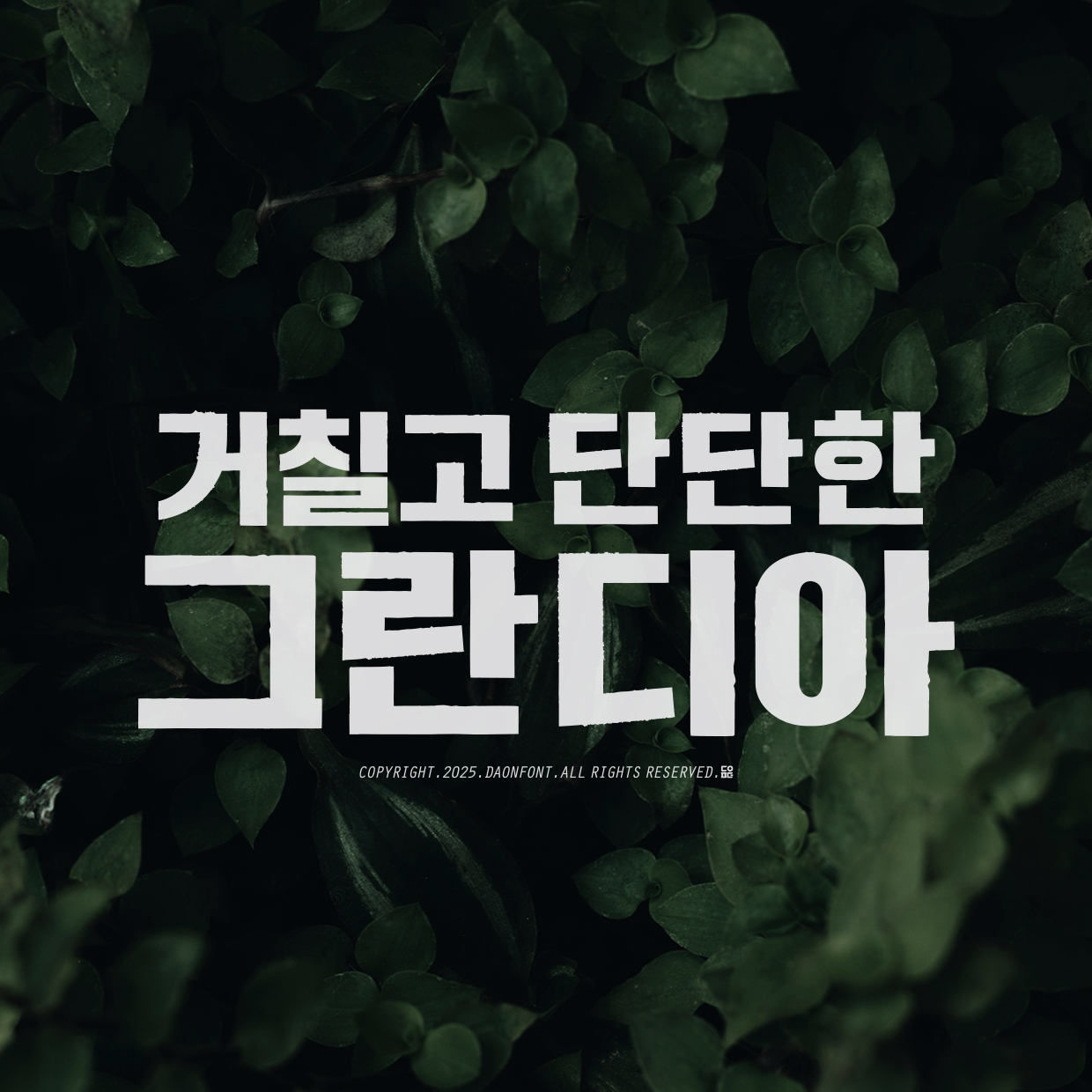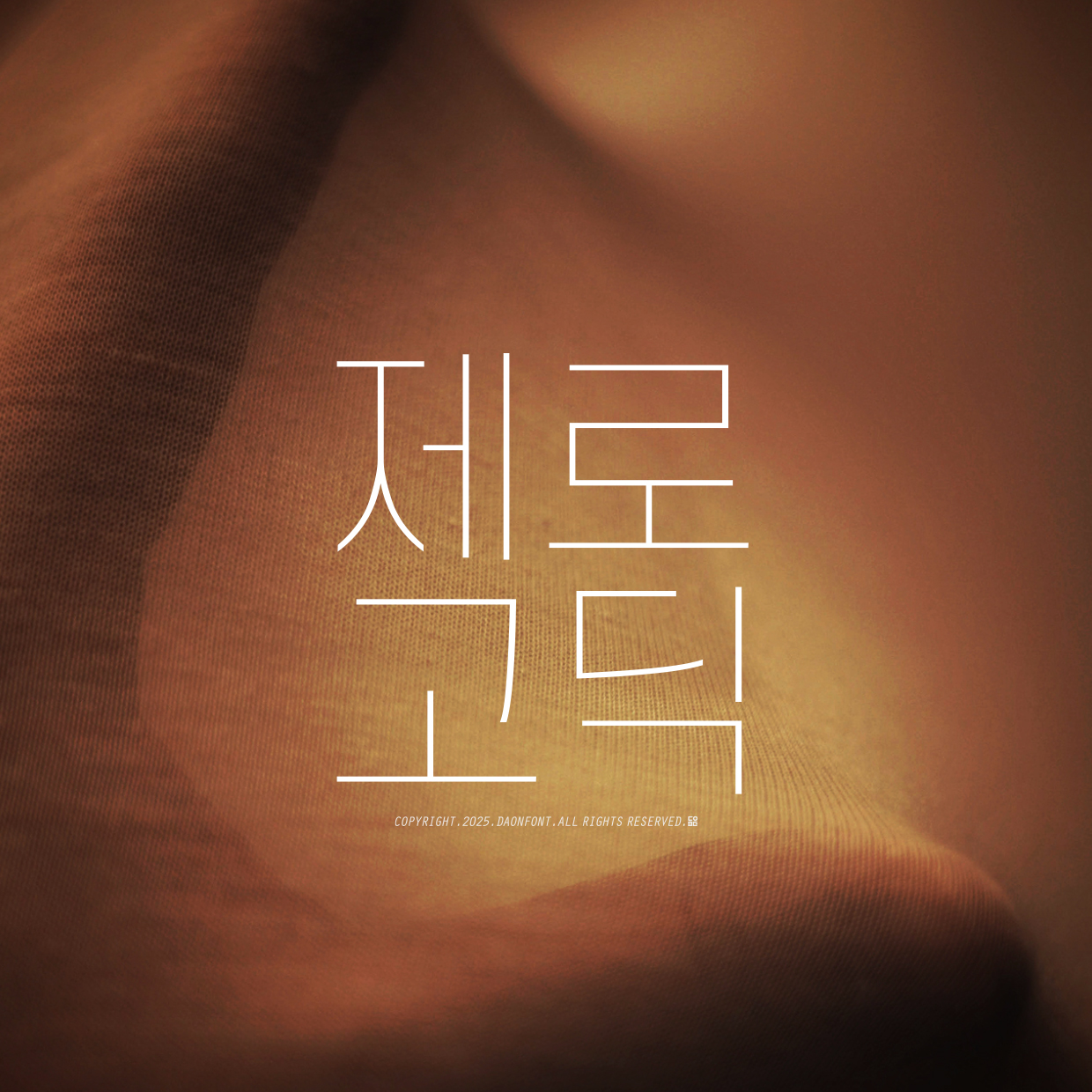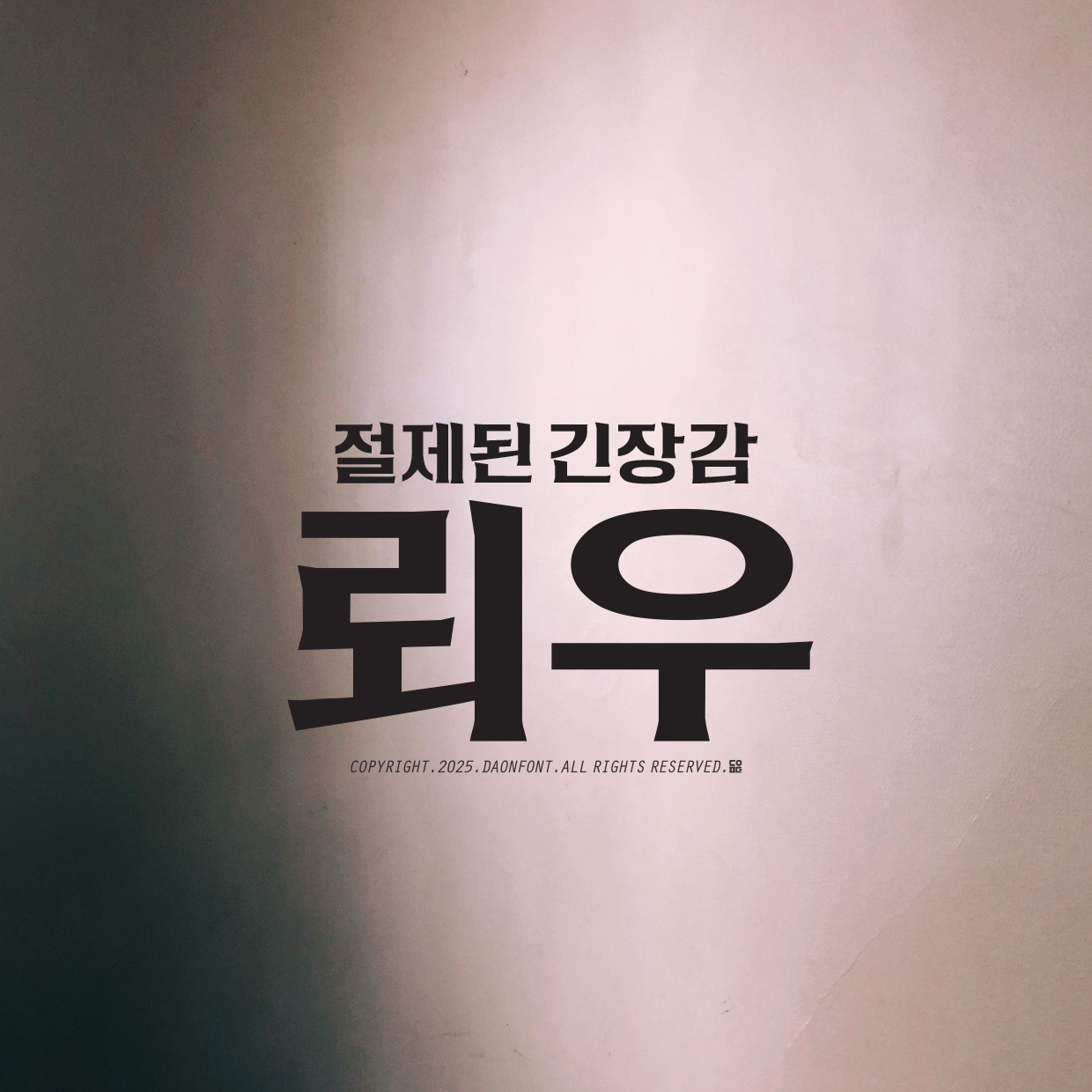
그란디아, 뢰우체, 제로고딕 5종 출시 안내
강하게, 섬세하게, 그리고 가볍게.
단단한 감성의 [그란디아], 절제된 부리의 [뢰우체 3종],
한글 타이포의 한계를 넘은 초슬림 [제로고딕]
새로운 폰트 5종이 4월 28일, 정식 출시됩니다.
디자인에 새로운 균형을 더할 서체들, 이제 곧 여러분을 찾아갑니다.